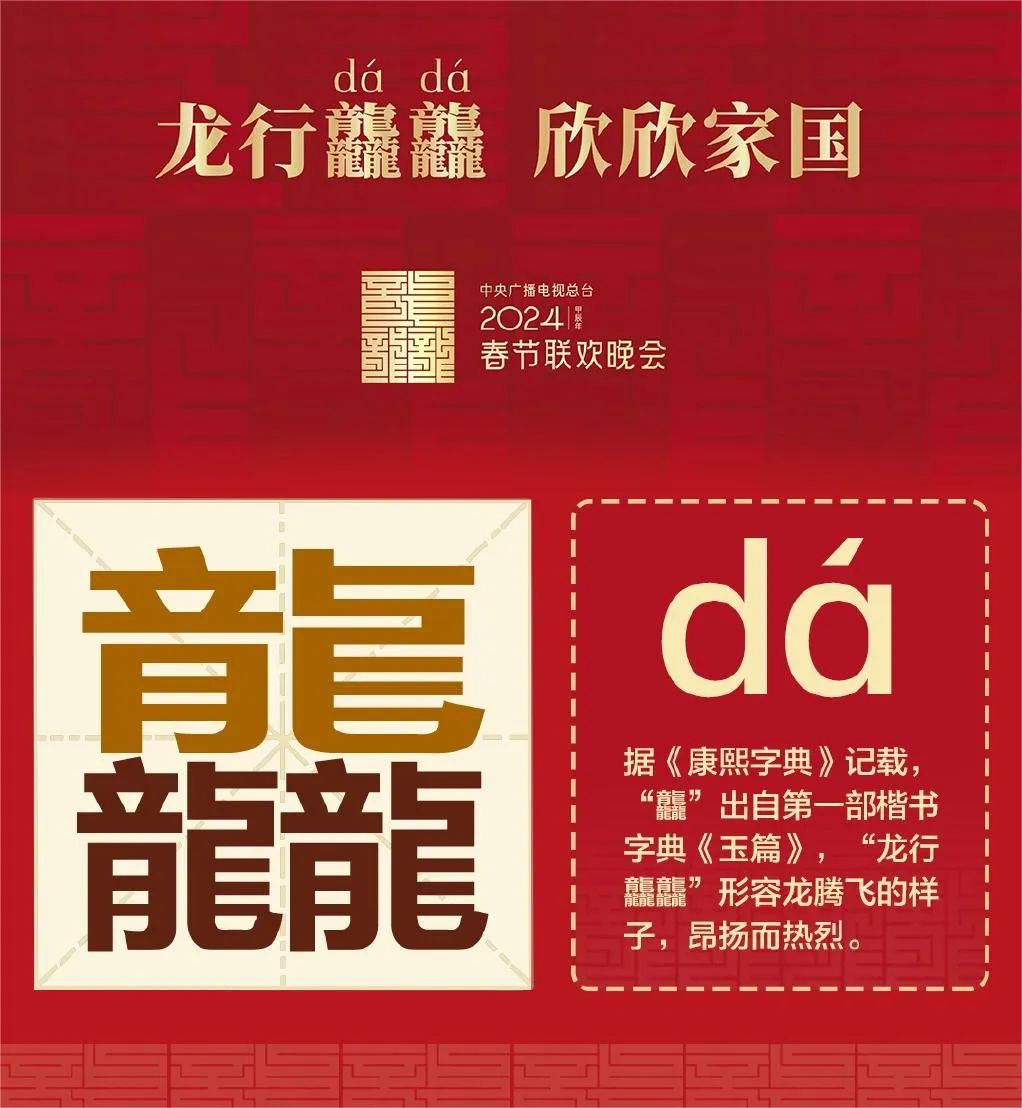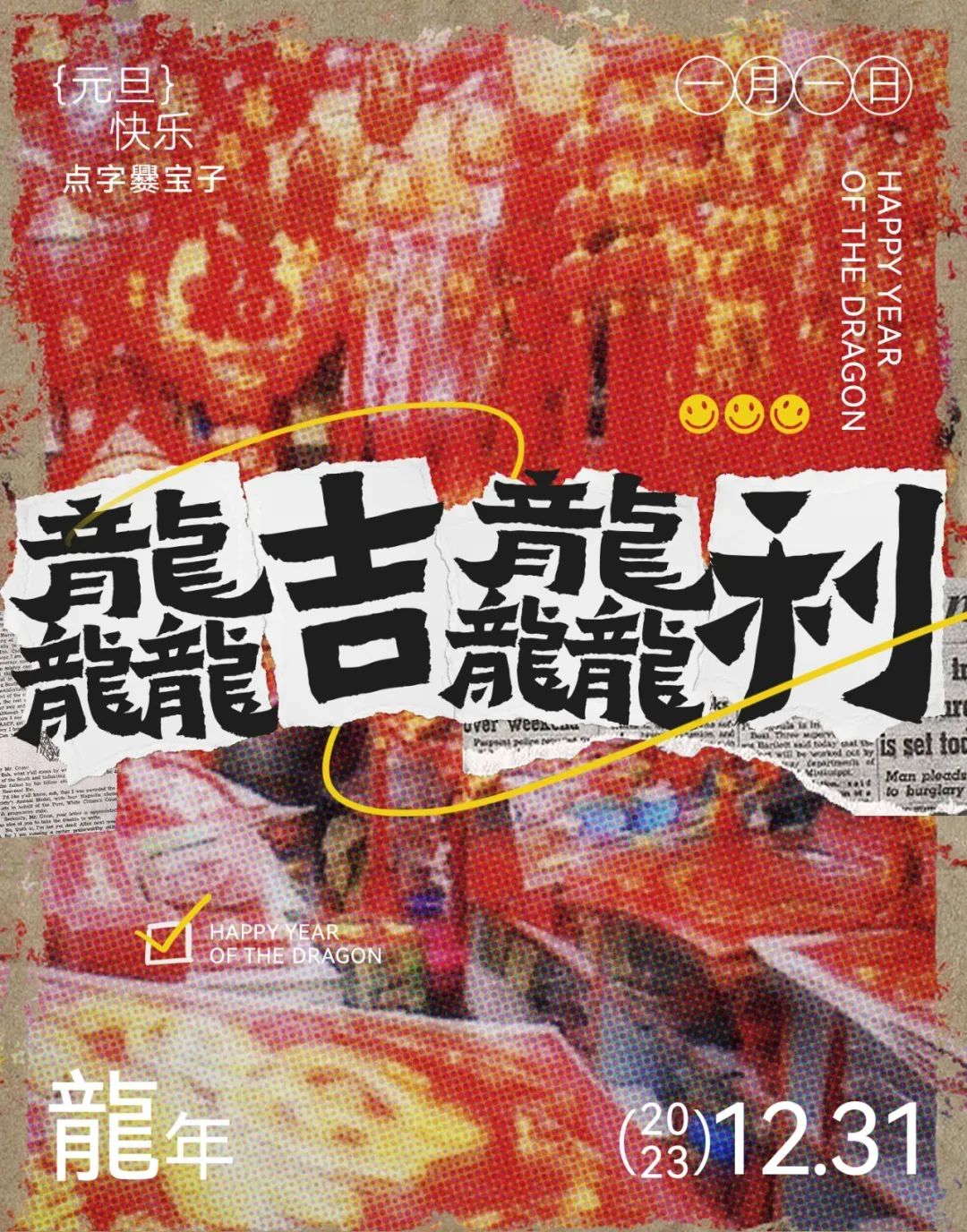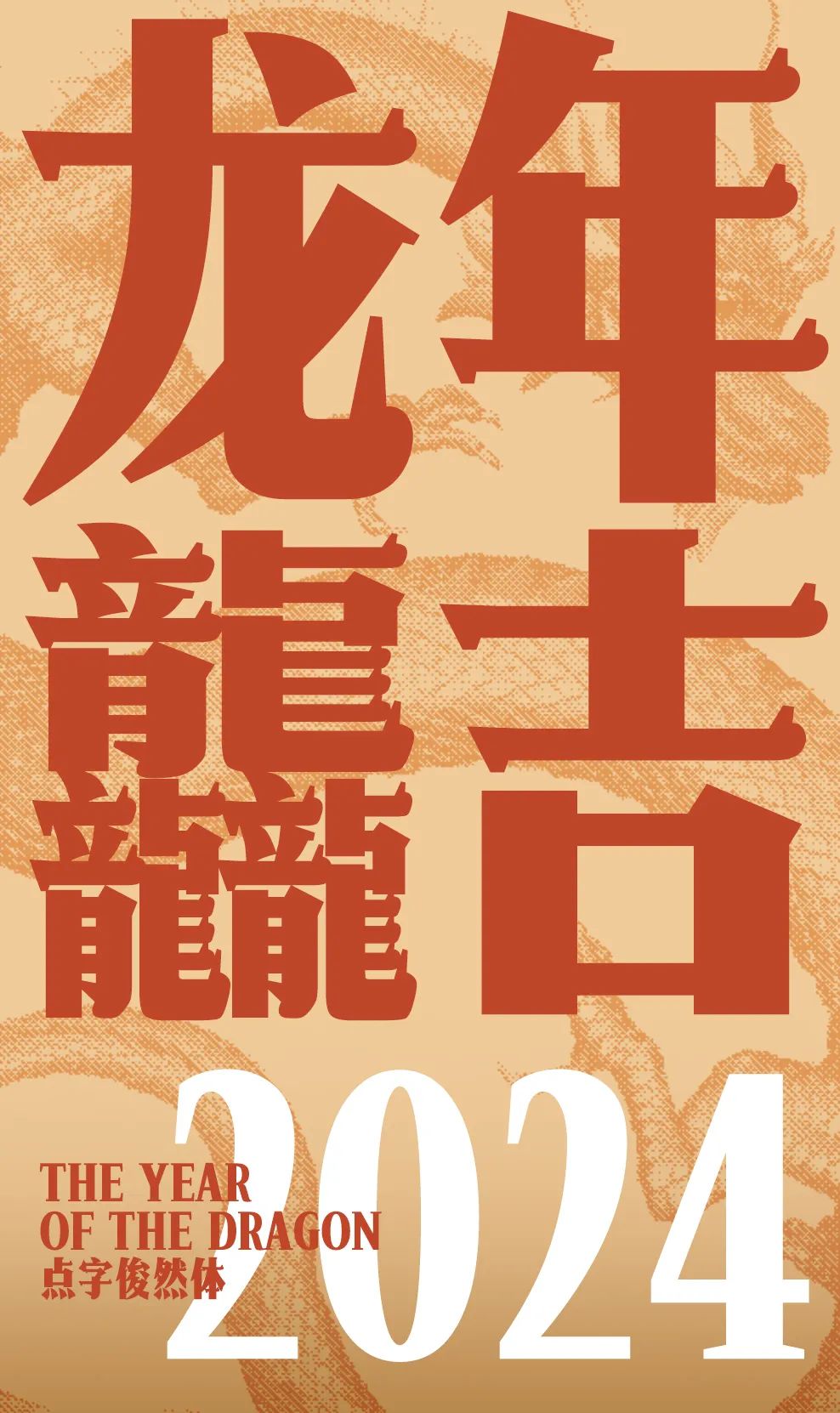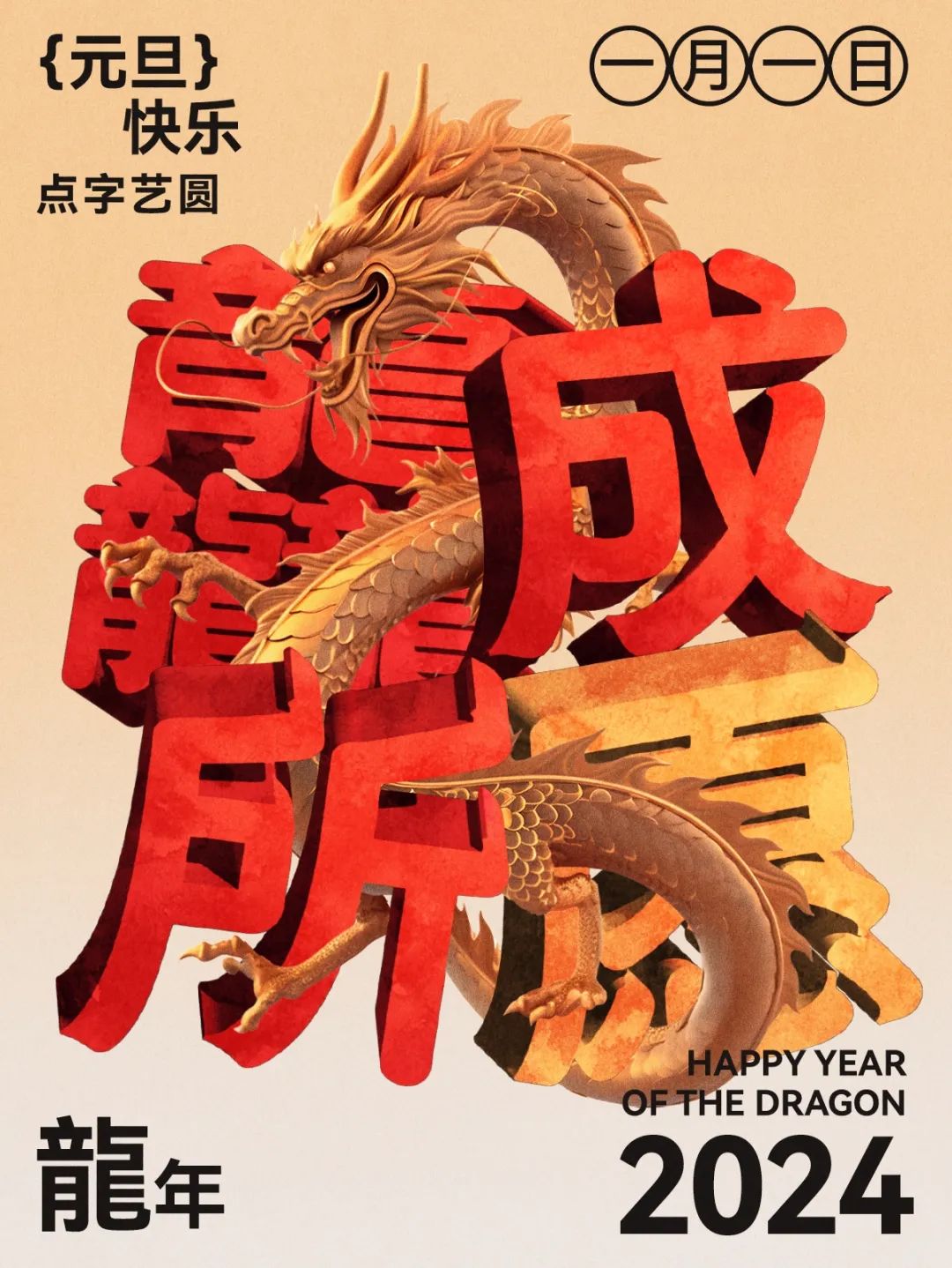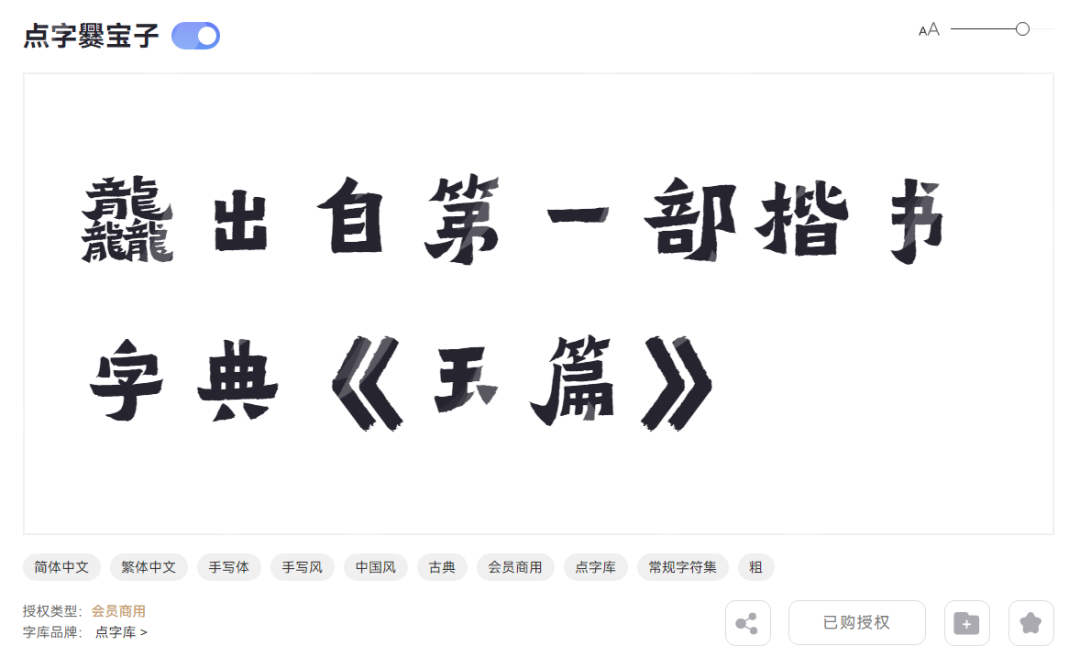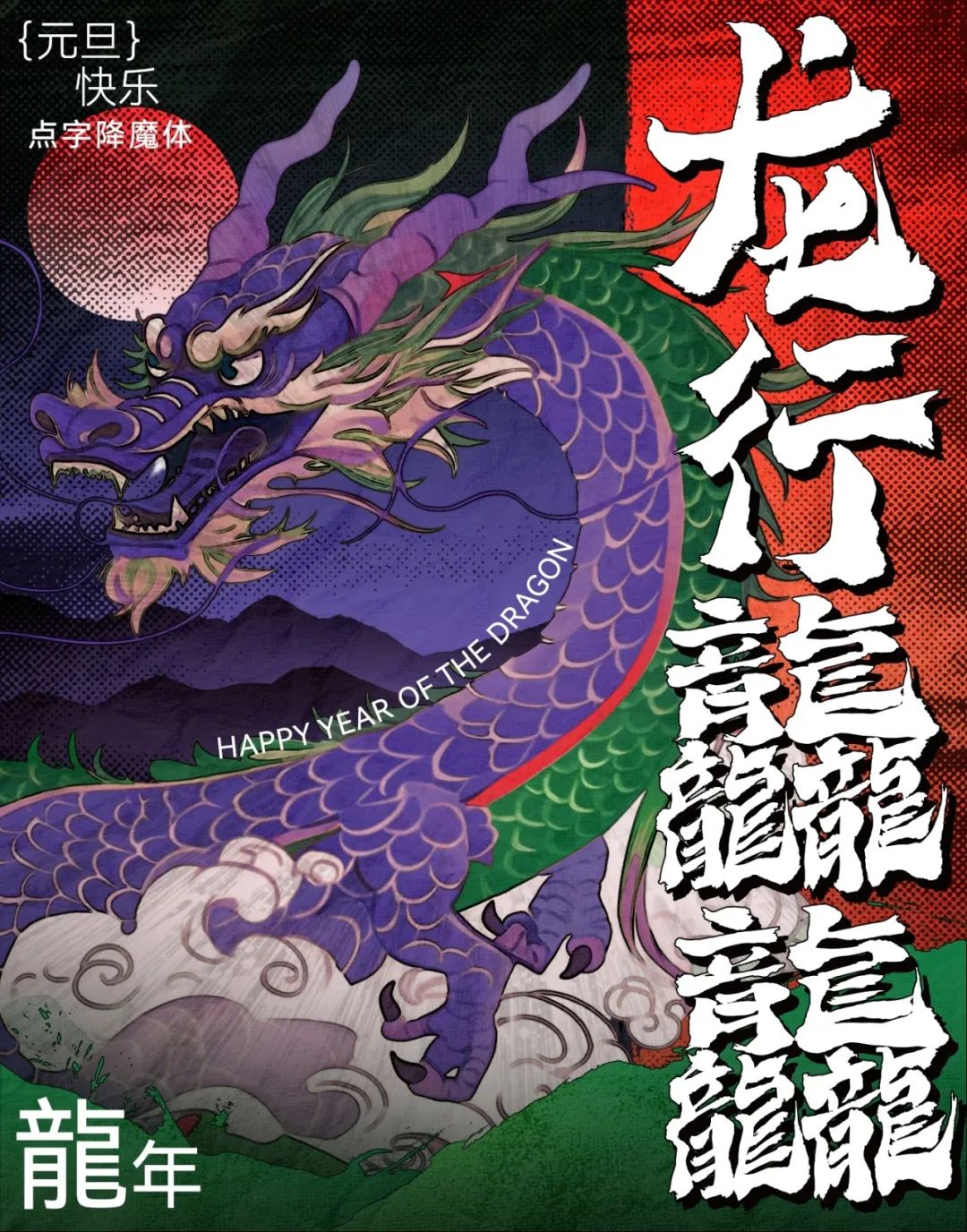
2024春晚主标识的“龘”,原来这么帅!
前一段时间,网上因为“龙辰辰”的AI感,产生了很大的争议。
其实你只要看下历年的春晚吉祥物,大概心里就有数了……
好不好看不重要,重要的是气氛担当(一不小心笑出了声)~
不过龙年的春晚主标识,倒是给了一个大大的惊喜!
直接用到了生僻字“龘”,来自康熙字典,寓意所有龙的传人一起腾飞。
跟以往的数字设计简直不是一个次元壁的……
这并不是设计师第一次把汉字融入主标识,早在兔年,就把草书的“卯”和兔圆圆结合在一起了。
而这次更有突破,不仅用到了不常见的“三条龍”,还以宋代国朝官印的九叠篆为灵感,汉字之美,传统文化,在这一刻都有了具象的符号。
看到这里,你是不是也想“龙行龘龘”(至少要能打出字来)了!
我懂,所以设计师拼着真元,增加了五款字体的“龘”。
除了以上五款,会员字体中还有三款本身就有“龘”字的。